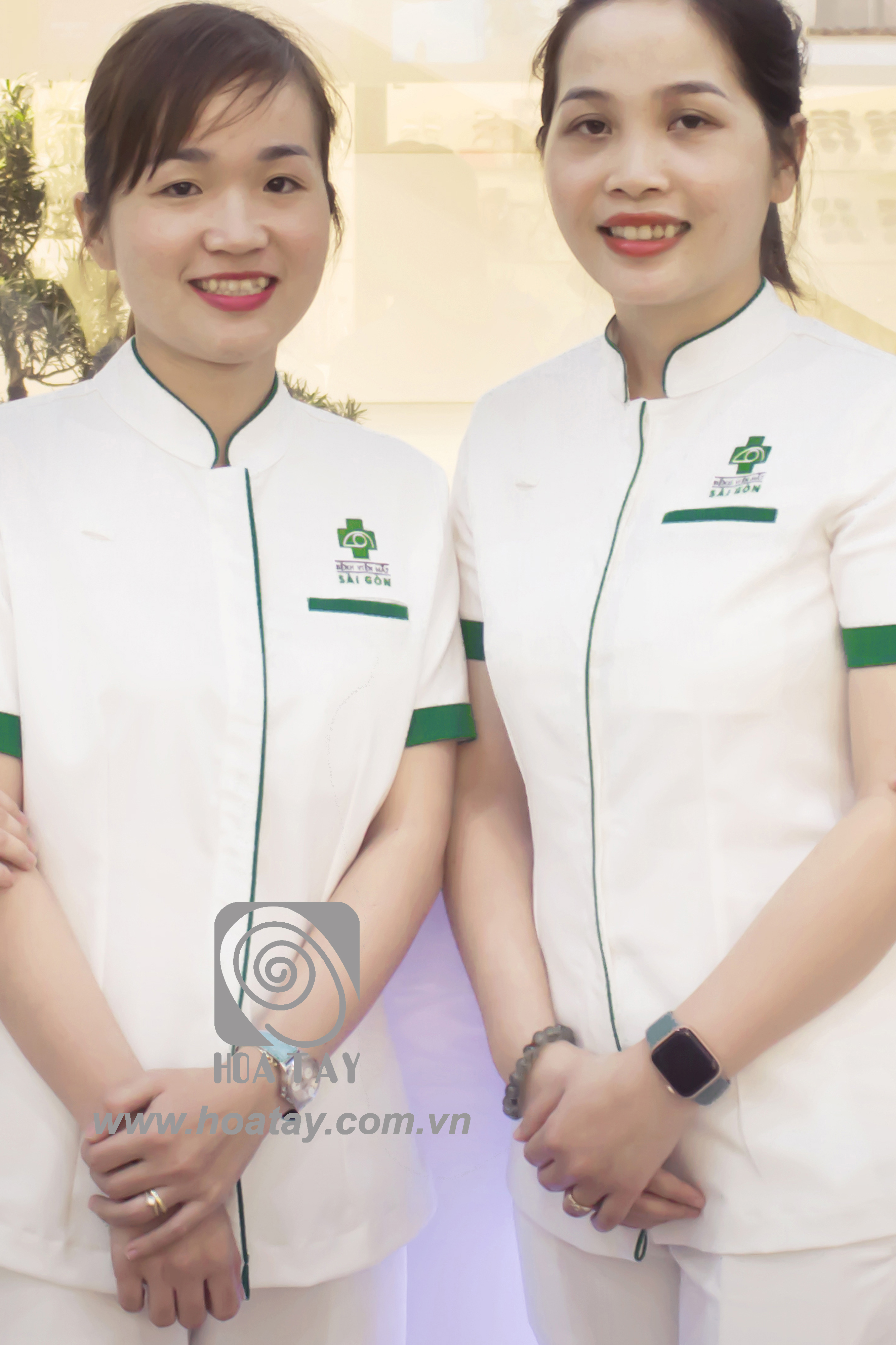
Bác sĩ đeo bảng tên sáng bóng, nhưng ngực áo blouse vẫn trống trơn. Chỉ cần thiếu một dòng chức danh, bộ đồng phục y tế lập tức mất đi vẻ chỉn chu cần có. Ngược lại, khi các ký tự được thể hiện đúng chuẩn thẩm mỹ, chúng không chỉ xác nhận vị thế học thuật mà còn tạo niềm tin tức thì cho người bệnh. Đây chính là sức nặng vô hình của font chữ thêu y khoa trên mỗi bộ thêu áo blouse bác sĩ. Nhiều tổ chức quan tâm đến chữ thêu trang trọng nhưng chưa rõ cách chọn mẫu phù hợp để cân bằng giữa tính hiện đại và sự nghiêm túc đặc thù của ngành y.
Vì sao font chữ quyết định sự trang trọng của chức danh?
Một dòng chữ “PGS.TS” hay “BS.CKII” trên ngực áo không đơn thuần là nhãn dán xác nhận danh xưng. Đó là bằng chứng ngoại hình cho học hàm và kinh nghiệm chuyên môn mà người mang blouse đã tích lũy trong nhiều năm. Khi một nhân viên y tế xuất hiện với dòng chữ chức danh được thể hiện rõ ràng, bệnh nhân nhận được tín hiệu trực quan về mức độ uy tín. Chính vì vậy, việc chọn đúng font chữ thêu y khoa không phải là chuyện thẩm mỹ phụ trợ, mà là yếu tố cốt lõi tạo nên sự tin cậy trong môi trường chăm sóc sức khỏe.
Sự khác biệt giữa “đẹp” và “trang trọng”
Trong ngữ cảnh y khoa, khái niệm “trang trọng” khác xa với cái “đẹp” theo nghĩa mỹ thuật thông thường. Một font chữ uốn lượn, cầu kỳ có thể trông nghệ thuật nhưng lại phá vỡ sự nghiêm túc cần thiết cho một bác sĩ hay giảng viên y.
Sự dễ đọc phải luôn được đặt lên hàng đầu. Khi bệnh nhân đứng từ xa hành lang bệnh viện, họ không có thời gian để thưởng thức nét uốn cong phức tạp; họ cần nhận diện nhanh thông tin. Một mẫu thêu chức danh đạt chuẩn phải đảm bảo các nét chỉ sắc bén, khoảng cách chữ đều đặn để mắt người đọc xử lý thông tin tức thì. Sự rõ ràng chính là nền tảng của sự tôn trọng dành cho đối phương.
Tác động lên nhận thức của bệnh nhân
Não bộ của con người đánh giá sự chuyên nghiệp qua những chi tiết nhỏ trước khi nghe một lời giải thích nào. Nếu dòng chữ thêu tên áo blouse bị méo, khó đọc hay dùng font thiếu uy tín, nó tạo ra một ấn tượng ban đầu tiêu cực về sự cẩu thả trong công việc. Ngược lại, một dòng chữ đứng thẳng, rõ ràng ngay lập tức nâng cao cảm giác an tâm của người bệnh.
Việc này ảnh hưởng trực tiếp đến tương tác giữa nhân viên y tế và bệnh nhân. Sự chỉn chu trong từng nét chỉ là lời giới thiệu thầm lặng nhưng mạnh mẽ nhất về tiêu chuẩn làm việc của tổ chức. Người đọc không cần phải là chuyên gia về thời trang để cảm nhận được sự khác biệt giữa một bộ đồng phục được chăm chút và một bộ đồng phục đại trà. Đó là lý do mà phòng nhân sự hay quản lý bệnh viện cần chú trọng đến tiêu chí chữ thêu trang trọng này khi xây dựng hình ảnh thương hiệu.
Arial, Helvetica hay chân mảnh: Font nào hợp với blouse y tế?
Khi xác định font chữ thêu y khoa, sự đơn giản và rõ nét luôn là tiêu chí hàng đầu. Với những chức danh dài như “BS.CKII” hay “PGS.TS”, các font không chân (sans-serif) như Arial và Helvetica là lựa chọn an toàn nhất. Chúng có cấu trúc nét thẳng, khoảng cách đều, giúp bệnh nhân đọc nhanh và chính xác từ khoảng cách xa. Đây là cách để mẫu thêu chức danh vừa hiện đại, vừa thể hiện được sự chuyên nghiệp cần có trong môi trường y tế.
Lựa chọn an toàn: Font không chân
Arial và Helvetica đã trở thành chuẩn mực trong thiết kế đồng phục y tế bởi khả năng giữ form tốt khi thêu. Các nét chữ không có chân thừa, giúp chỉ không bị rối trên bề mặt vải mỏng như Mango hay Nano. Khi thêu tên áo blouse, loại font này tạo cảm giác thoáng, sạch sẽ, tránh được sự nặng nề vốn có của các dòng chữ phức tạp.
Phương án thay thế: Font chân mảnh
Nếu tổ chức muốn tạo điểm nhấn học thuật hoặc cổ điển hơn, font có chân mảnh nhẹ (thin-serif) là một phương án đáng cân nhắc. Tuy nhiên, cần đảm bảo nét chân không quá dày. Trong kỹ thuật thêu, các chi tiết quá nhỏ dễ bị lem hoặc không hiển thị rõ khi giặt. Một dòng chữ thêu trang trọng cần sự cân bằng giữa tính thẩm mỹ và độ bền, tránh những nét chân quá mảnh gây khó đọc.
Nên tránh: Font uốn lượn cầu kỳ
Không nên sử dụng các font script hoặc decorative cho thêu áo blouse bác sĩ. Những kiểu chữ uốn lượn làm giảm khả năng đọc nhanh, tạo cảm giác thiếu nghiêm túc trong bối cảnh bệnh viện bận rộn. Một mẫu thêu chức danh đẹp không nằm ở sự phức tạp của nét vẽ, mà ở khả năng truyền tải thông tin một cách rõ ràng, tôn trọng người đọc và nâng tầm hình ảnh của nhân viên y tế.
Kỹ thuật thêu: Độ cao, nét chỉ và vị trí ngực trái
Độ cao của dòng chữ thêu trên áo blouse không chỉ là vấn đề thẩm mỹ mà còn ảnh hưởng trực tiếp đến khả năng đọc từ khoảng cách ngắn. Trong thực hành thêu tên áo blouse, mức độ cao tiêu chuẩn cho một dòng chức danh thường nằm trong khoảng 1–1,5cm. Con số này đủ lớn để người đối diện nhận diện thông tin khi tiếp xúc gần, nhưng vẫn đủ nhỏ để không phá vỡ sự cân đối của vùng ngực áo. Khoảng cách giữa các dòng (nếu thêu hai dòng tên và chức danh) nên được căn đều, tránh tạo cảm giác chật chội hoặc quá rời rạc.
Ảnh hưởng của chất liệu vải đến độ sắc nét
Không phải loại vải nào cũng phản ánh nét chỉ với độ chính xác như nhau. Chất liệu quyết định lực thêu mà máy cần áp dụng, từ đó tác động đến độ nổi và độ sắc của font chữ. Với các loại vải như Kaki Hàn, bề mặt dày vừa và giữ form tốt giúp kim thêu bám chắc, tạo ra các nét chỉ rõ ràng, không bị bẹt. Ngược lại, vải Mango có bề mặt trơn và nhẹ hơn, đòi hỏi điều chỉnh lực thêu thấp hơn để tránh làm cứng vải hoặc gây co rút. Kỹ thuật này đảm bảo rằng dù là áo blouse cho bác sĩ nam hay nữ, mẫu thêu chức danh vẫn giữ được sự tinh tế và sắc nét đặc trưng của chữ thêu trang trọng.
Sự chỉn chu đến từ những quyết định nhỏ nhất: một dòng chữ chức danh rõ ràng, cân đối và bền bỉ qua nhiều lần giặt. Nó nhắc nhở người đối diện rằng họ đang được chăm sóc bởi một đội ngũ chuyên nghiệp, nơi mọi thứ đều được cân nhắc kỹ lưỡng. Hãy để bộ đồng phục kể câu chuyện về sự tỉ mỉ và uy tín của tổ chức, một cách tự nhiên và đầy tâm sức.